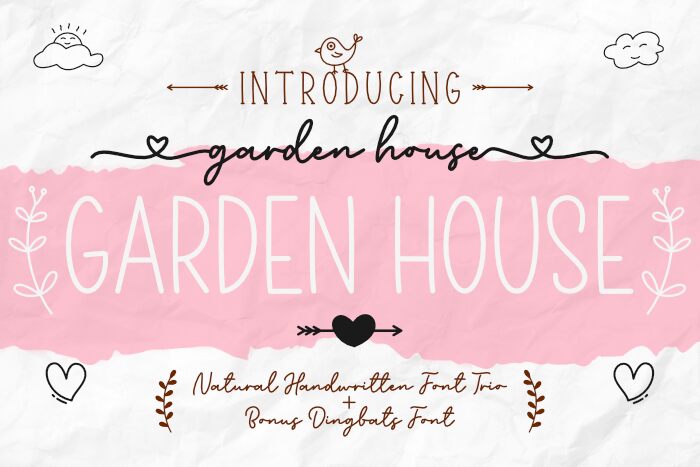
Garden House Signature par Madatype Studio est une police signature au pinceau gratuite, dotée de boucles amples et d'un tracé manuscrit fluide. Les lettres liées évoluent le long d'une ligne légèrement irrégulière, avec de longs traits d'attaque et de fuite qui rappellent un tracé rapide à la plume. Les variations d'épaisseur de trait maintiennent la vivacité de l'écriture plutôt qu'un aspect mécanique.
Les thèmes de la romance, de la beauté et des célébrations personnelles s'accordent avec son style intime, ce qui la rend utile pour les faire-part de mariage, l'emballage de boutiques, l'identité visuelle de mode et les visuels pour réseaux sociaux. Les fioritures prolongées évoquent des rubans, des tiges ou de fines illustrations au trait, permettant ainsi au lettrage de faire partie intégrante de l'illustration.